I en verden hvor vores smartphones er blevet vores primære adgang til internettet, er det afgørende, at din hjemmeside præsenterer sit indhold fejlfrit og læsevenligt på små skærme. Squarespace er kendt for sin brugervenlighed og sit responsive design, som automatisk tilpasser dit site til forskellige enheder. Men hvad gør du, når du har brug for en mere præcis kontrol over skriftstørrelsen, især på mobil, for at sikre den absolut bedste brugeroplevelse? Selvom Squarespaces indbyggede stilredigering håndterer meget, giver den sjældent den finejustering, der kan være nødvendig for at opnå et perfekt mobilt udseende. Denne guide vil dykke ned i, hvordan du med brugerdefineret CSS kan skræddersy din skriftstørrelse specifikt til mobile enheder, og derved løfte din hjemmesides æstetik og funktionalitet til et nyt niveau.
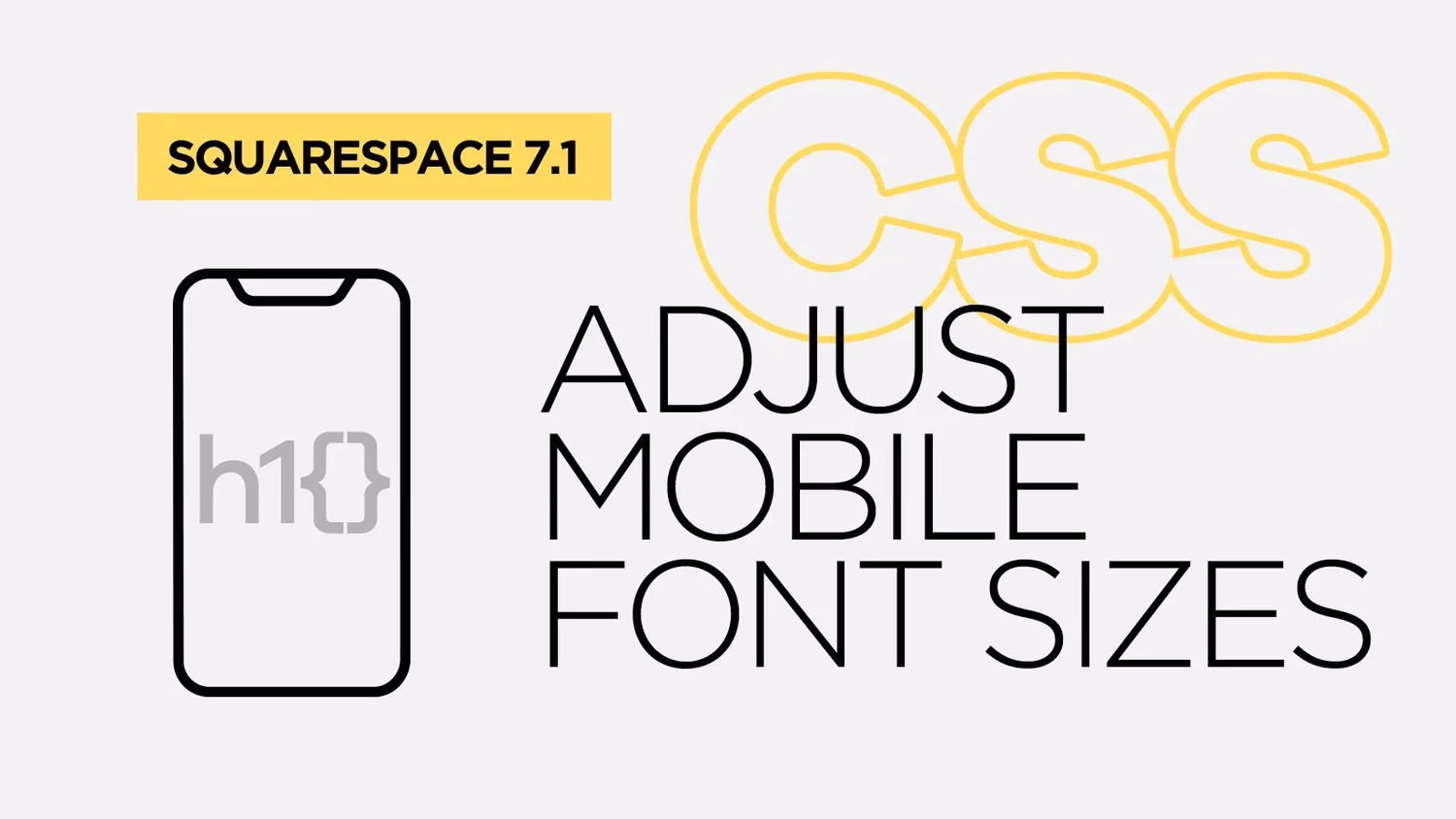
Hvorfor er Mobilvenlig Skriftstørrelse Afgørende?
Mobile enheder står for en stadig større del af internettrafikken – for mange hjemmesider udgør det over halvdelen. Dette betyder, at dine besøgende sandsynligvis vil opleve dit indhold på en lille skærm. Hvis teksten er for lille, for tæt pakket eller svær at læse, vil de hurtigt forlade din side. Dette har flere negative konsekvenser:
- Dårlig brugeroplevelse (UX): Frustrerede besøgende vender ikke tilbage. En god læseoplevelse er fundamental for at holde dem engagerede.
- Forringet SEO: Google prioriterer mobilvenlige hjemmesider. En høj afvisningsprocent (bounce rate) og kort besøgstid på grund af dårlig læsbarhed kan skade din placering i søgeresultaterne.
- Professionelt image: En hjemmeside, der ser rodet eller uprofessionel ud på mobil, afspejler dårligt på dit brand eller din virksomhed.
At have fuld kontrol over skriftstørrelsen på mobil er altså ikke kun et spørgsmål om æstetik; det er en direkte investering i din hjemmesides succes og dine besøgendes tilfredshed.
Squarespace's Standard Håndtering af Skriftstørrelser
Squarespace er bygget med responsivt design i tankerne. Det betyder, at når du vælger en skrifttype og størrelse i stilredigeringsprogrammet, vil systemet automatisk forsøge at tilpasse den til forskellige skærmstørrelser, herunder tablets og smartphones. Dette er en fantastisk grundfunktion, der sikrer, at dit indhold generelt ser fornuftigt ud på de fleste enheder uden yderligere indgriben. Problemet opstår, når 'fornuftigt' ikke er godt nok. Måske er din overskrift for stor og fylder for meget plads på en lille skærm, eller din brødtekst er lige akkurat for lille til at være behagelig at læse, selvom Squarespace har justeret den ned. Den indbyggede stilredigering giver dig ofte mulighed for at indstille en 'base' skriftstørrelse for brødtekst og overskrifter, men sjældent med separate, præcise kontroller specifikt for mobil. Dette er her, hvor brugerdefineret CSS kommer ind som en kraftfuld løsning.
Trin-for-Trin Guide: Juster Skriftstørrelse med Brugerdefineret CSS
For at opnå den præcise kontrol, du ønsker, skal vi anvende brugerdefineret CSS-kode. Bare rolig, det er nemmere, end det lyder, og du behøver ikke at være en programmør for at følge med.
- Åbn CSS-editoren i Squarespace:
Dette åbner et vindue, hvor du kan indsætte din egen CSS-kode, som vil overskrive eller supplere Squarespaces standardstilarter.
- Identificer de Elementer, du Vil Målrette: Før du kan ændre skriftstørrelsen, skal du vide, hvilket specifikt element du vil ændre. De mest almindelige er:
- Paragraffer (brødtekst):
p - Overskrifter:
h1,h2,h3,h4 - Listeelementer:
li - Knapper: Ofte har de en specifik klasse, f.eks.
.sqs-block-button .sqs-button-element - Specifikke blokke: Du kan ofte finde en CSS-klasse for en specifik tekstblok, f.eks.
.sqs-block-contenteller en mere specifik id, hvis du bruger udviklerværktøjer i din browser (højreklik > 'Inspicer element').
- Paragraffer (brødtekst):
- Anvend Media Queries til Mobil-Specifikke Ændringer: Dette er det afgørende skridt for at sikre, at dine ændringer kun gælder for mobile enheder. Media Queries giver os mulighed for at anvende CSS-regler baseret på skærmstørrelsen. For mobil bruger vi typisk en
max-width(maksimal bredde). En almindelig breakpoint for mobile enheder er 767px eller 640px. Eksempelkode:@media screen and (max-width: 767px) { /* Her indsættes din mobil-specifikke CSS */ p { font-size: 16px !important; /* Brødtekst på mobil */ line-height: 1.6em !important; /* Juster linjeafstand for bedre læsbarhed */ } h2 { font-size: 24px !important; /* Overskrift H2 på mobil */ } h3 { font-size: 20px !important; /* Overskrift H3 på mobil */ } /* Hvis du vil målrette en specifik knaptekst */ .sqs-block-button .sqs-button-element { font-size: 18px !important; } /* Hvis du vil målrette tekst i en specifik indholdsblok */ .sqs-block-html .sqs-block-content p { font-size: 15px !important; } }Forklaring af koden:
@media screen and (max-width: 767px) { ... }: Dette fortæller browseren, at de CSS-regler, der er inde i disse klammeparenteser, kun skal anvendes, når skærmbredden er 767 pixels eller mindre (typisk smartphones og små tablets i portrættilstand).p { font-size: 16px !important; }: Dette ændrer skriftstørrelsen for alle paragraffer til 16 pixels.!important-deklarationen er ofte nødvendig i Squarespace for at sikre, at din brugerdefinerede CSS overskriver Squarespaces standardstilarter. Brug den dog med forsigtighed, da den kan gøre det sværere at overskrive stilarter senere.line-height: Justerer afstanden mellem tekstlinjerne, hvilket kan forbedre læsbarheden markant på små skærme.
- Test og Juster: Når du har indsat koden, skal du gemme og derefter teste din hjemmeside på en rigtig mobiltelefon eller bruge din browsers udviklerværktøjer til at simulere forskellige mobilskærme. Juster
font-size-værdierne, indtil du er tilfreds med udseendet og læsbarheden. Prøv forskellige enheder for at sikre, at det ser godt ud på tværs af mange skærmstørrelser.
Avancerede Tips til CSS-Tilpasning
Udover de grundlæggende ændringer er der flere måder at finjustere din typografi på mobil:
- Brug Relative Enheder: I stedet for faste pixelstørrelser (
px), kan du overveje at bruge relative enheder somem,remellervw(viewport width).em: Relativ til forælderelementets skriftstørrelse.rem: Relativ til rodbasisskriftstørrelsen (oftehtml-elementets skriftstørrelse). Dette er ofte mere forudsigeligt endem.vw: Relativ til viewportens bredde. F.eks. vil2vwbetyde 2% af skærmens bredde, hvilket kan give en meget flydende tilpasning.
Eksempel med
rem:@media screen and (max-width: 767px) { p { font-size: 1rem !important; /* 1rem er typisk 16px, men følger rodbasisskriftstørrelsen */ } h2 { font-size: 1.5rem !important; } } - Målret Specifikke Sektioner: Hvis du kun vil ændre skriftstørrelsen i en bestemt sektion eller blok, skal du finde dens unikke ID eller klasse. Du kan gøre dette ved at bruge 'Inspicer element' i din browser.
@media screen and (max-width: 767px) { #block-yui_3_17_2_1_1608678900123_4567 .sqs-block-content p { font-size: 14px !important; } }(Bemærk: Blok-ID'er som dette er ofte dynamiske og kan ændre sig, så vær forsigtig med at bruge dem. Klasser er ofte mere stabile.)
- Overvej Linjehøjde og Margen: Udover skriftstørrelse kan justering af
line-heightogmargin-bottom(mellem paragraffer) forbedre læsbarheden markant på små skærme. En god tommelfingerregel er enline-heightpå omkring 1.5 til 1.8 for brødtekst.
Husk at bruge !important sparsomt, da det kan gøre din CSS sværere at vedligeholde. Brug det kun, når du absolut skal overskrive en eksisterende stil.
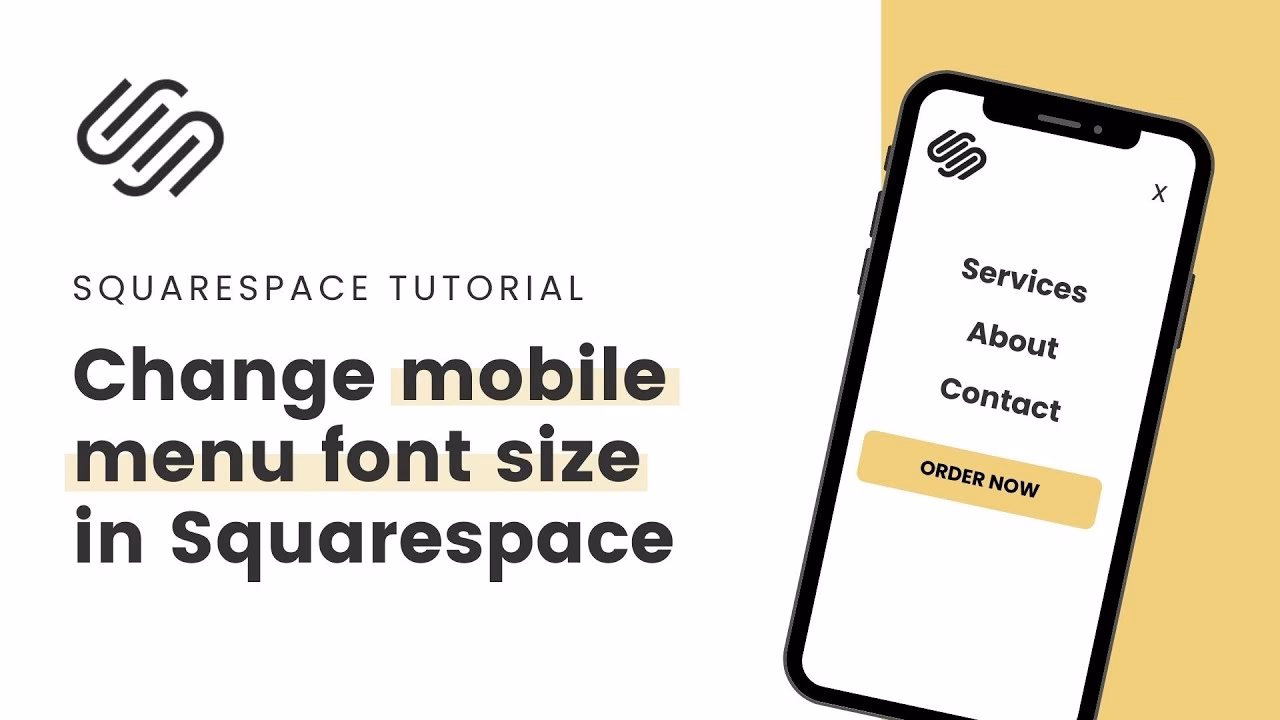
Forståelse af Skrifttyper på Squarespace: Mere end blot Størrelse
Mens justering af skriftstørrelse er kritisk, er valget af selve skrifttyper (font families) lige så vigtigt for din hjemmesides udseende og følelse. Squarespace tilbyder en omfattende samling af skrifttyper, herunder et bredt udvalg af Google Fonts samt premium Adobe Fonts, som giver dig rig mulighed for at finde den perfekte typografi til dit brand. Skrifttyper formidler stemning, stil og professionalisme, og det rigtige valg kan forbedre læsbarheden og dit visuelle udtryk dramatisk. Hver skrifttype har sin egen unikke personlighed og anvendelsesmuligheder.
Udvalgte Skrifttyper og Deres Anvendelse på Squarespace
Squarespace giver dig adgang til et væld af skrifttyper, men nogle skiller sig ud for deres specifikke egenskaber og evne til at skabe en bestemt stemning. Lad os se nærmere på et par eksempler, der kan give din hjemmeside et moderne, klassisk og luksuriøst præg:
- Nueva Std Extended: Denne skrifttype, der stammer fra Adobe-familien, udstråler en moderne, men klassisk elegance. Den er perfekt til at give din hjemmeside en sofistikeret stemning. Nueva Std Extended fungerer fremragende til overskrifter, hvor den kan fange opmærksomheden, men den er også yderst læsevenlig i brødtekst. Med 18 forskellige stilarter at vælge imellem har du stor fleksibilitet til at tilpasse den præcist til dit design. Dens klarhed og rene linjer gør den ideel til brands, der ønsker at formidle kvalitet og raffinement.
- Broadacre: Hvis du søger en skrifttype med en kurvet, luksuriøs følelse, er Broadacre et fremragende valg. Den har en unik måde at lege med vægten på, hvor siderne af hvert bogstav fortykkes, mens andre forbliver tynde. Dette skaber en dynamisk og indbydende tekst, der opfordrer læseren til at fortsætte. Broadacre er især effektiv, når den bruges til at skabe en blød, men alligevel iøjnefaldende effekt, og dens 'light 0' stil kan give et let og luftigt udtryk. Denne skrifttype egner sig godt til branding, hvor et strejf af eksklusivitet er ønskeligt, og dens læsevenlighed gør den også velegnet til længere tekstpassager.
- Roc Grotesk: Inspireret af amerikansk trætypografi fra det 19. århundrede, er Roc Grotesk designet til at gøre et dristigt statement. Med hele 45 stilarter og ni vægte kan du finde den perfekte variant til at skabe en stærk visuel effekt. Roc Grotesk er ideel til call-to-action knapper, vigtige overskrifter eller sektioner, hvor du ønsker at fange brugerens opmærksomhed og formidle en følelse af autoritet. Den er fantastisk til at skabe kontrast og tilføje en moderne kant til et ellers klassisk design. Dens alsidighed og styrke gør den til et uundværligt værktøj for designere, der ønsker at skabe en mindeværdig typografi.
Kombinationen af disse skrifttyper – f.eks. Nueva Std Extended til overskrifter, Broadacre til brødtekst og Roc Grotesk til handlingsfremmende elementer – kan skabe en moderne, klassisk og luksuriøs stemning, der er ideel for luksus- og detailvirksomheder.
| Skrifttypenavn | Stilkarakteristik | Anbefalet Anvendelse | Antal Stilarter / Vægte |
|---|---|---|---|
| Nueva Std Extended | Klassisk, sofistikeret, ren | Overskrifter, brødtekst for et elegant look | 18 stilarter |
| Broadacre | Kurvet, luksuriøs, dynamisk vægtspil | Brødtekst for god læsbarhed, branding med eksklusivitet | Varierende vægte, f.eks. 'light 0' |
| Roc Grotesk | Fed, dristig, moderne, autoritativ | Call-to-action, vigtige overskrifter, statement-tekst | 45 stilarter, 9 vægte |
Ofte Stillede Spørgsmål om Skriftstørrelse og Skrifttyper på Squarespace
- Q: Kan jeg ændre skriftstørrelsen for *hele* min hjemmeside på én gang med CSS?
- A: Ja, du kan målrette generelle elementer som
bodyellerpfor at ændre den grundlæggende skriftstørrelse for hele hjemmesiden. Men for mobil er det bedst at gøre det inden for en Media Query for at sikre, at ændringerne kun gælder for mindre skærme og ikke påvirker dit desktop-design. - Q: Hvad er en "media query"?
- A: En media query er en CSS-teknik, der giver dig mulighed for at anvende forskellige stilarter baseret på enhedens egenskaber, såsom skærmbredde, højde eller orientering. Det er fundamentalt for responsivt design, da det lader din hjemmeside tilpasse sig perfekt til alle skærmstørrelser.
- Q: Hvorfor virker min CSS ikke?
- A: Der kan være flere grunde:
- Syntaksfejl: Tjek for stavefejl, manglende semikoloner eller klammeparenteser.
- Specifikke vælgere: Din CSS-vælger er måske ikke specifik nok. Squarespaces standardstilarter kan være mere specifikke. Prøv at tilføje
!importantefter din stil (f.eks.font-size: 16px !important;), men brug det med omtanke. - Cache: Nogle gange kan browserens cache forhindre dig i at se de seneste ændringer. Prøv at rydde din browsercache eller se siden i inkognitotilstand.
- Blok-ID'er: Hvis du bruger et blok-ID, skal du sikre dig, at det er korrekt og stadig aktuelt, da disse kan ændre sig.
- Q: Er det kun skriftstørrelse, jeg kan justere med CSS?
- A: Absolut ikke! Med brugerdefineret CSS kan du justere stort set alle visuelle aspekter af din hjemmeside: farver, baggrunde, margener, polstring, linjeafstand, skrifttyper, knapstilarter og meget mere. Det er et utroligt kraftfuldt værktøj til at finjustere dit Squarespace-design.
- Q: Hvor mange Google Fonts er der på Squarespace?
- A: Squarespace integrerer en omfattende samling af både Google Fonts og Adobe Fonts i deres platform. Mens et præcist tal kan variere, opdateres og udvides biblioteket løbende, hvilket giver Squarespace-brugere adgang til hundredvis af skrifttyper til at skræddersy deres hjemmesider. Du vil finde et bredt udvalg, der dækker stort set alle designbehov.
Konklusion
At mestre skriftstørrelsen på mobile enheder på din Squarespace hjemmeside er en lille, men utroligt virkningsfuld detalje, der kan løfte din brugeroplevelse markant. Selvom Squarespace gør et fremragende stykke arbejde med responsivt design, giver den brugerdefinerede CSS dig den præcision, der skal til for at skabe et poleret og professionelt udseende på enhver skærm. Ved at følge denne guide og eksperimentere med CSS, kan du sikre, at dit indhold ikke kun er smukt, men også letlæseligt og engagerende for alle dine besøgende, uanset hvordan de tilgår din side. En veloptimeret mobiloplevelse er nøglen til succes i den digitale verden.